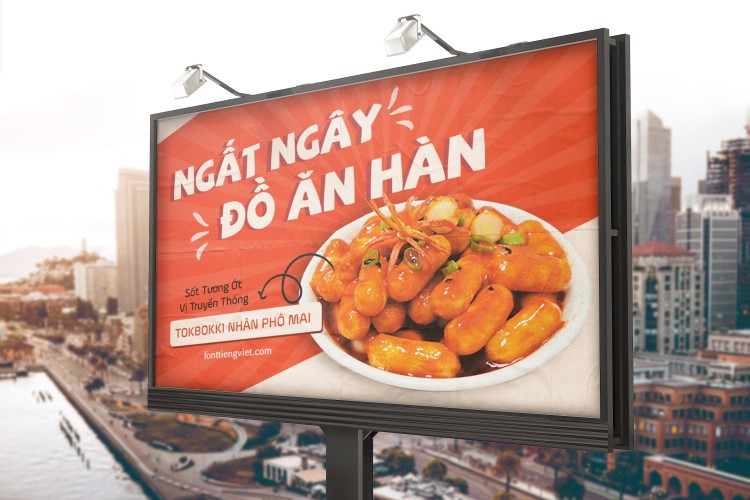
Combo font thiết kế ẩm thực 1 – Sẳn hiệu ứng trong file Ps
Combo font thiết kế ẩm thực 1 – Sẳn hiệu ứng trong file Ps mang đến giải pháp đồ họa chuyên nghiệp và tiện lợi nhất cho cộng đồng sáng tạo tại Việt Nam. Trong lĩnh vực thiết kế menu hay poster quảng cáo đồ ăn, việc lựa chọn Font Miễn Phí phù hợp đóng vai trò then chốt giúp kích thích vị giác và thu hút khách hàng ngay từ cái nhìn đầu tiên. Bộ sưu tập này không chỉ cung cấp những phông chữ đẹp mắt mà còn tích hợp sẵn các hiệu ứng đổ bóng, tạo khối và màu sắc rực rỡ trực tiếp trong định dạng Photoshop. Điều này giúp các bạn học sinh, sinh viên và những người mới bắt đầu làm quen với thiết kế có thể tạo ra những sản phẩm chất lượng cao mà không tốn quá nhiều thời gian xử lý kỹ thuật phức tạp.
Lợi ích khi sử dụng Combo font thiết kế ẩm thực 1 – Sẳn hiệu ứng trong file Ps
Sự ra đời của bộ Combo font thiết kế ẩm thực 1 – Sẳn hiệu ứng trong file Ps đã giải quyết triệt để bài toán về tốc độ và thẩm mỹ trong thiết kế quảng cáo thực phẩm. Thông thường, để tạo ra một dòng chữ có hiệu ứng bắt mắt như ánh kim, đổ bóng 3D hay chất liệu gỗ, người thiết kế phải thực hiện rất nhiều bước Layer Style phức tạp. Tuy nhiên, với bộ combo này, mọi thông số đã được thiết lập sẵn một cách tinh tế nhất.
Đặc điểm nổi bật của bộ Font Việt hóa chuyên dụng cho ngành ăn uống
Một trong những điểm mạnh nhất của Combo font thiết kế ẩm thực 1 – Sẳn hiệu ứng trong file Ps chính là việc các phông chữ đã được Việt hóa hoàn chỉnh. Việc thiếu hụt các bộ font hỗ trợ dấu tiếng Việt luôn là rào cản lớn đối với các nhà thiết kế trong nước. Với bộ sưu tập này, bạn hoàn toàn yên tâm về việc hiển thị nội dung tiếng Việt chuẩn xác, không bị lỗi font hay mất dấu khi soạn thảo các thực đơn phong phú của Việt Nam.
Phong cách thiết kế đa dạng và hiện đại
Bộ combo tập hợp nhiều phong cách khác nhau từ nét chữ viết tay mềm mại, uốn lượn dành cho các món tráng miệng đến những kiểu chữ dày, chắc chắn cho các món nướng và thức ăn nhanh. Mỗi phông chữ đều mang một linh hồn riêng, giúp truyền tải thông điệp về hương vị và phong cách của thương hiệu một cách trọn vẹn. Hình ảnh minh họa đi kèm trong file cũng giúp người dùng dễ dàng hình dung cách phối hợp màu sắc sao cho hài hòa với tổng thể bức ảnh món ăn.
Mẹo nhỏ để có tác phẩm ấn tượng hơn
Mặc dù bộ combo đã có sẵn hiệu ứng, nhưng bạn vẫn có thể kết hợp thêm các yếu tố trang trí như lá cây, gia vị hoặc vệt nước sốt xung quanh chữ để tạo chiều sâu. Việc sử dụng ánh sáng phù hợp giữa chữ và nền sẽ giúp nội dung nổi bật hơn hẳn. Hãy nhớ rằng mục tiêu cuối cùng của thiết kế ẩm thực là làm cho thực khách cảm thấy đói và muốn thưởng thức món ăn ngay lập tức. Với bộ công cụ này, việc đạt được mục tiêu đó trở nên dễ dàng hơn bao giờ hết.